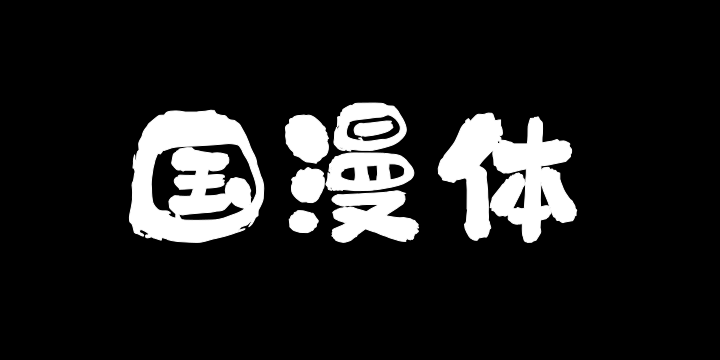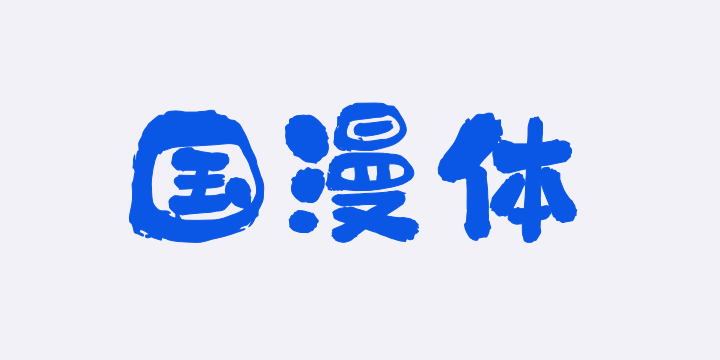
上首国漫体 By 上首造字 商用字体
字体全名: 上首国漫体
铸字厂: 上首造字
设计师: 胡博剑
字体简介: 上首国漫体,简体中文约6763字,该字体的设计灵感来源于传统中国书法和篆刻艺术,旨在融合古典与现代的美感,创造出一种具有深厚文化底蕴且富有表现力的字体。这种字体非常适合用于艺术设计、海报制作、书籍封面、品牌标识等需要突出个性和视觉冲击力的场合。